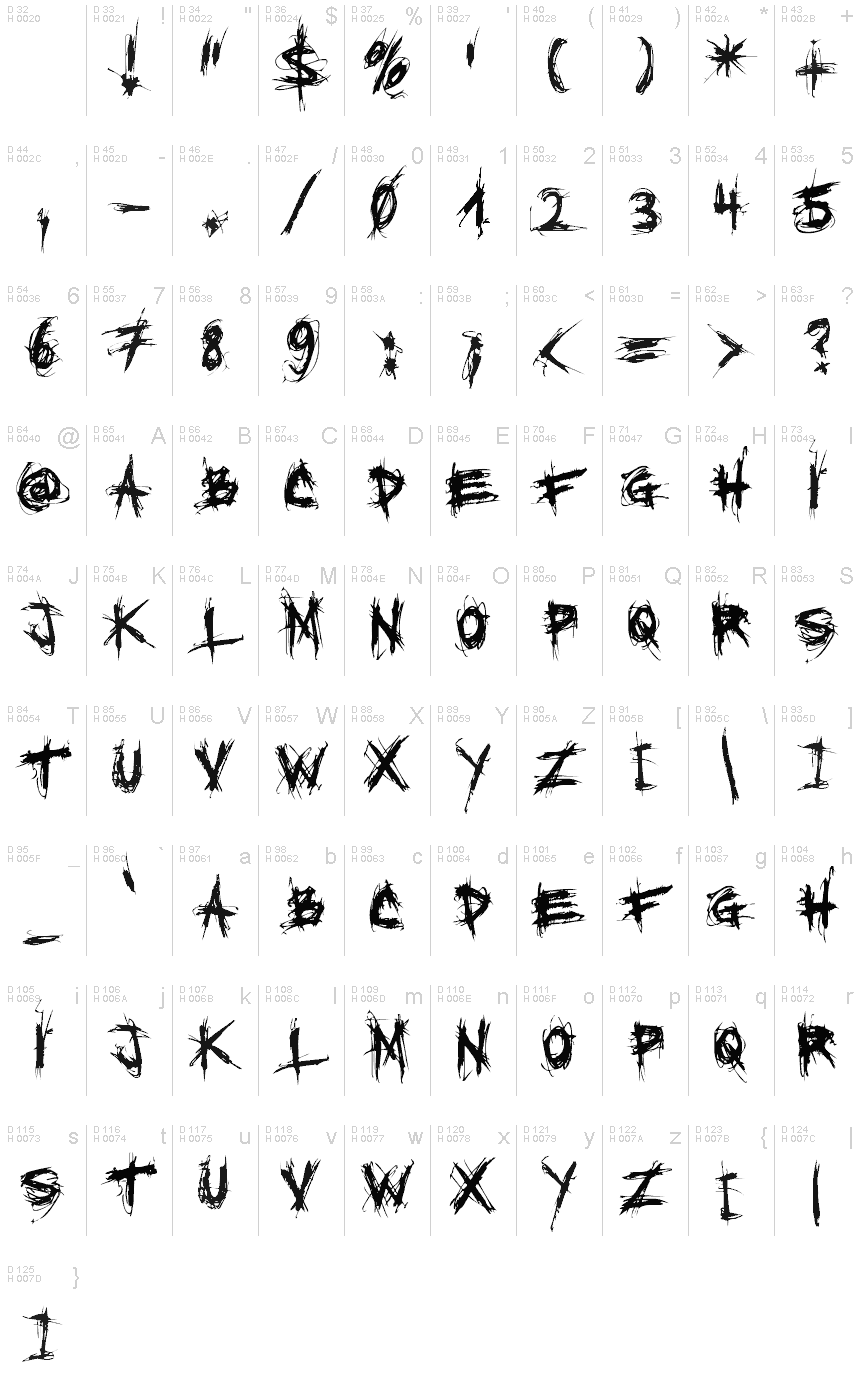
由 Lecter Johnson 设计的 XXII Scratch 是一款免费的 Trash Display 字体。它有着锯齿状和被切割的视觉外观,仿佛是由快速的刀痕和干笔触拼凑而成。字母呈现出撕裂的边缘、交错的划痕和混乱的重叠,赋予了这款字体 21 世纪初那种原始的 Grunge 风格能量,而非整齐划一的构造节奏。
它非常适合用于音乐传单、滑板图形、恐怖杂志、游戏标题卡以及叛逆风格的标题,让文字显得沧桑、不稳定且张力十足。作为一款免费字体,它也非常适合用于短篇海报标题、Logo 实验和字母组合,因为仅仅几个字母就能营造出一种由切痕和动感交织而成的浓郁氛围。